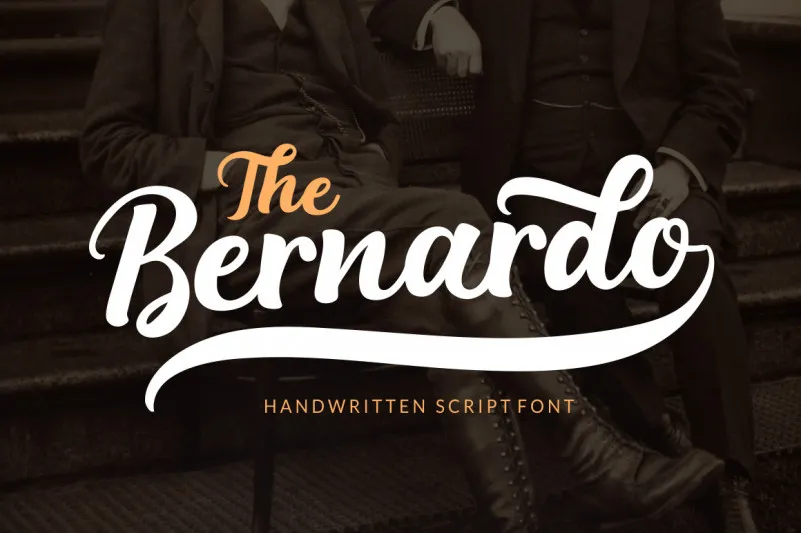
The Bernardo Font – Download Grátis
A fonte The Bernardo é uma beleza feita à mão, com traços fluidos e elegantes. Esta fonte enriquece projetos de headlines e logotipos dê-lhes um toque sofisticado. Ela traz uma forte sensação de confiança e dinamismo para seus designs. O Bernardo é PUA encoded o que significa que você pode acessar todas as letras e traços flutuantes com facilidade, adicionando um toque nostálgico a suas criações. Esta fonte brush estilizada é ideal para aqueles que procuram adicionar uma pitada de personalização à suas produções digitais. Sempre em busca de inspiração, o designer ReyreyBlue criou algo realmente especial com The Bernardo Font.